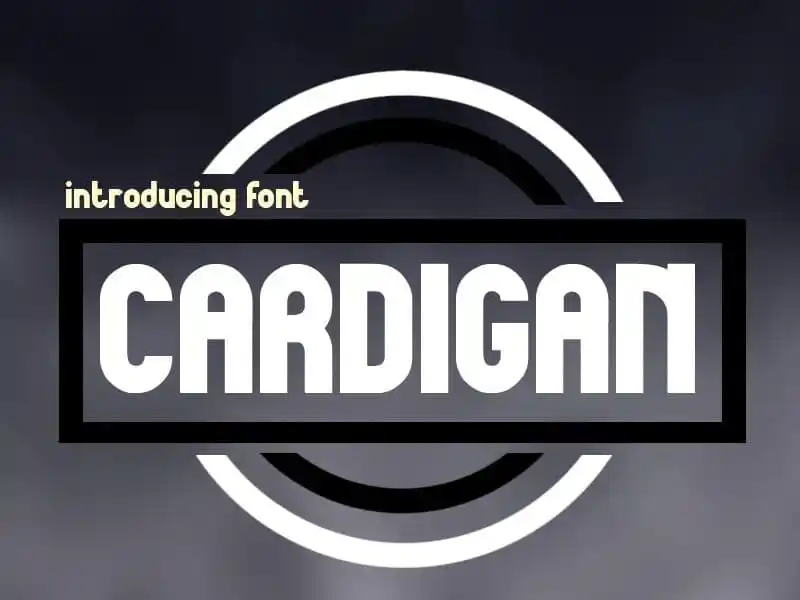
A Cardigan Display Font é uma escolha perfeita para designers que procuram um estilo moderno e elegante. Desenhada pelo sartstudio, esta fonte está disponível tanto como tipo de linha quanto em formatos web-fonts, o que a torna extremamente versátil para diferentes tamanhos e aplicações. Seja você querendo usar-a na criação de marcas ou logos, no destaque de uma frase ou até mesmo como um overlay de texto elegante sobre qualquer imagem de fundo, a Cardigan Display Font tem tudo o que precisa. Suavemente minimalista mas altamente sofisticada, ela se encaixa perfeitamente em design gráfico e estável para títulos e captions. Com uma aparência limpa e moderna, é ideal para transformar qualquer projeto de design em um elemento único e chamativo.